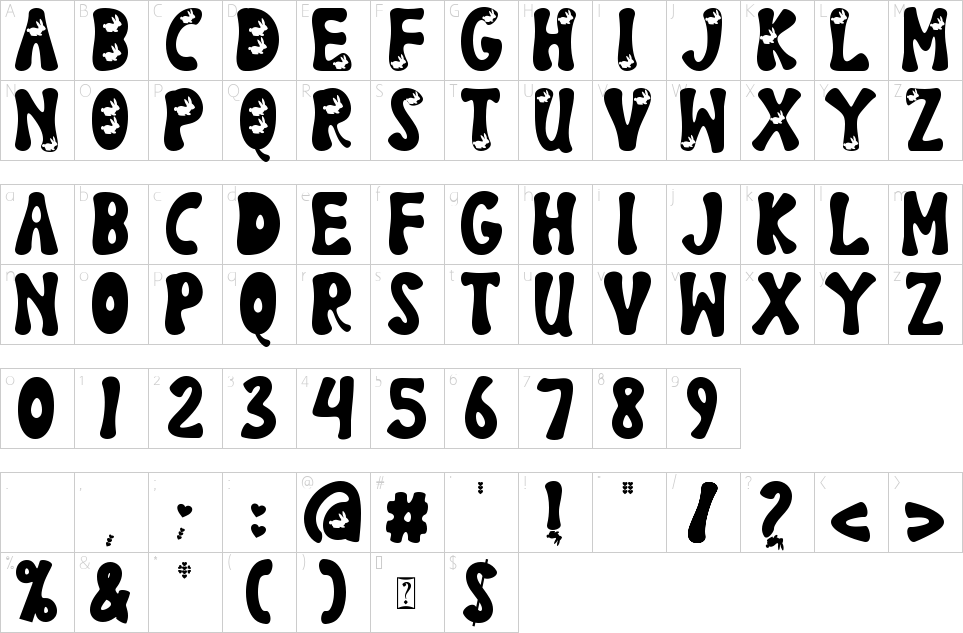
Easter Rabbit Font – Download Grátis
Descubra a encantadora Easter Rabbit Font, uma seleção elegante para aqueles que desejam adicionar algo especial aos seus projetos digitais. Essa fonte foi criada pela Yoga Letter e está disponível de forma gratuita tanto para Windows quanto para Mac. Com seu design delicado e atraente, a Easter Rabbit Font é perfeita para criar um toque alegre e encantador em qualquer projeto gráfico. Com apenas 2,922 downloads, você faz parte do seleto grupo que já experimentou este charmoso recurso de fontes grátis. Adquira-a agora e traga um toque único ao seu próximo design!